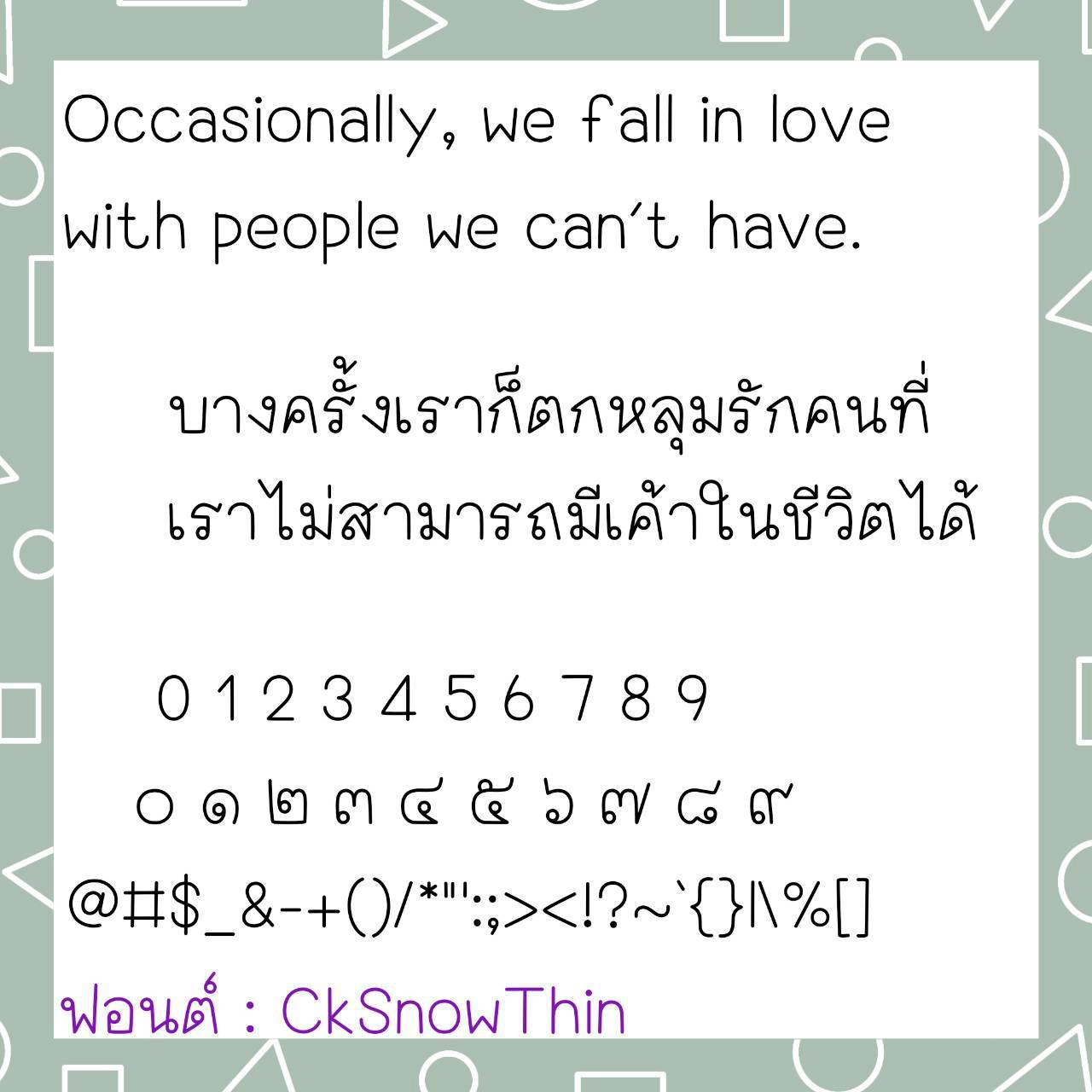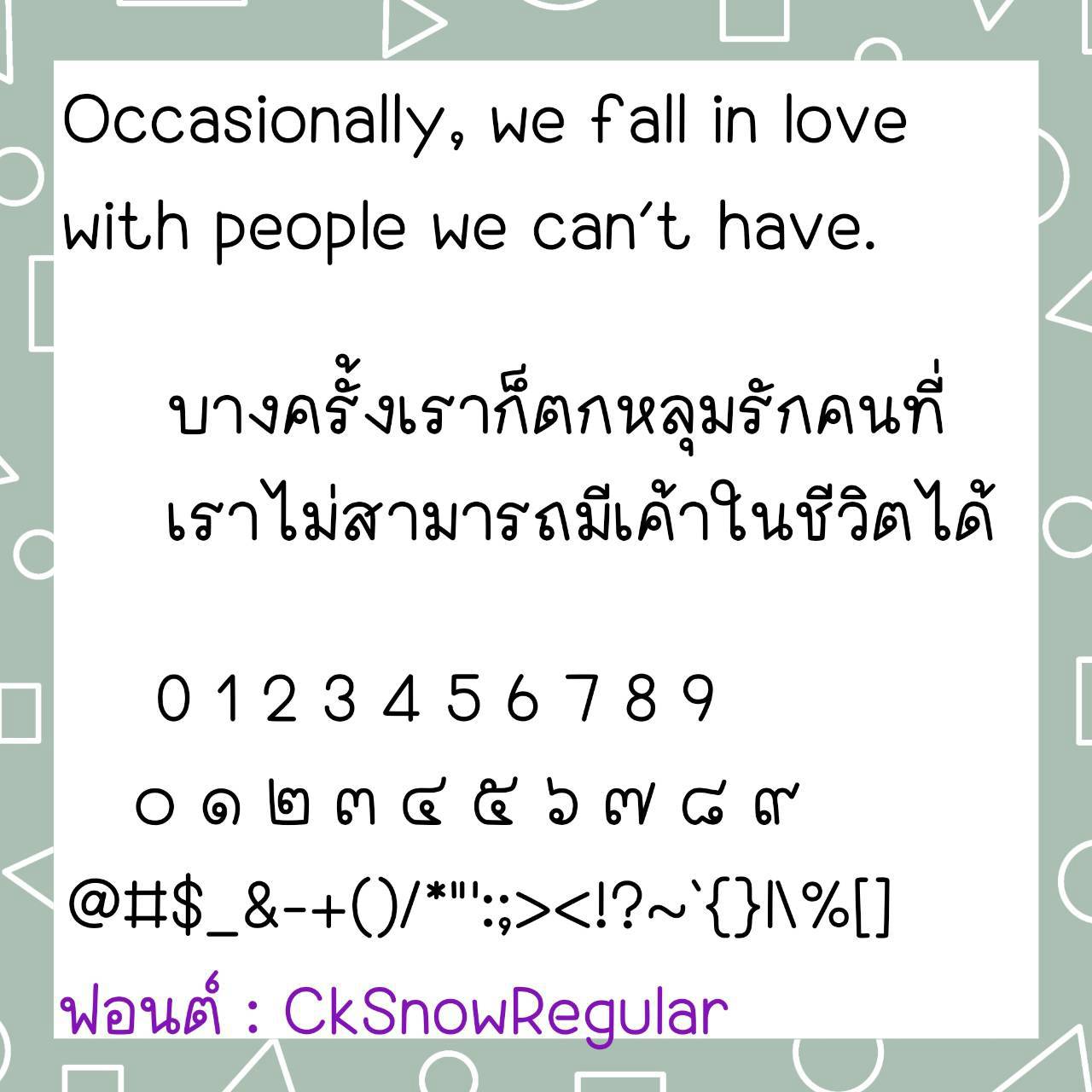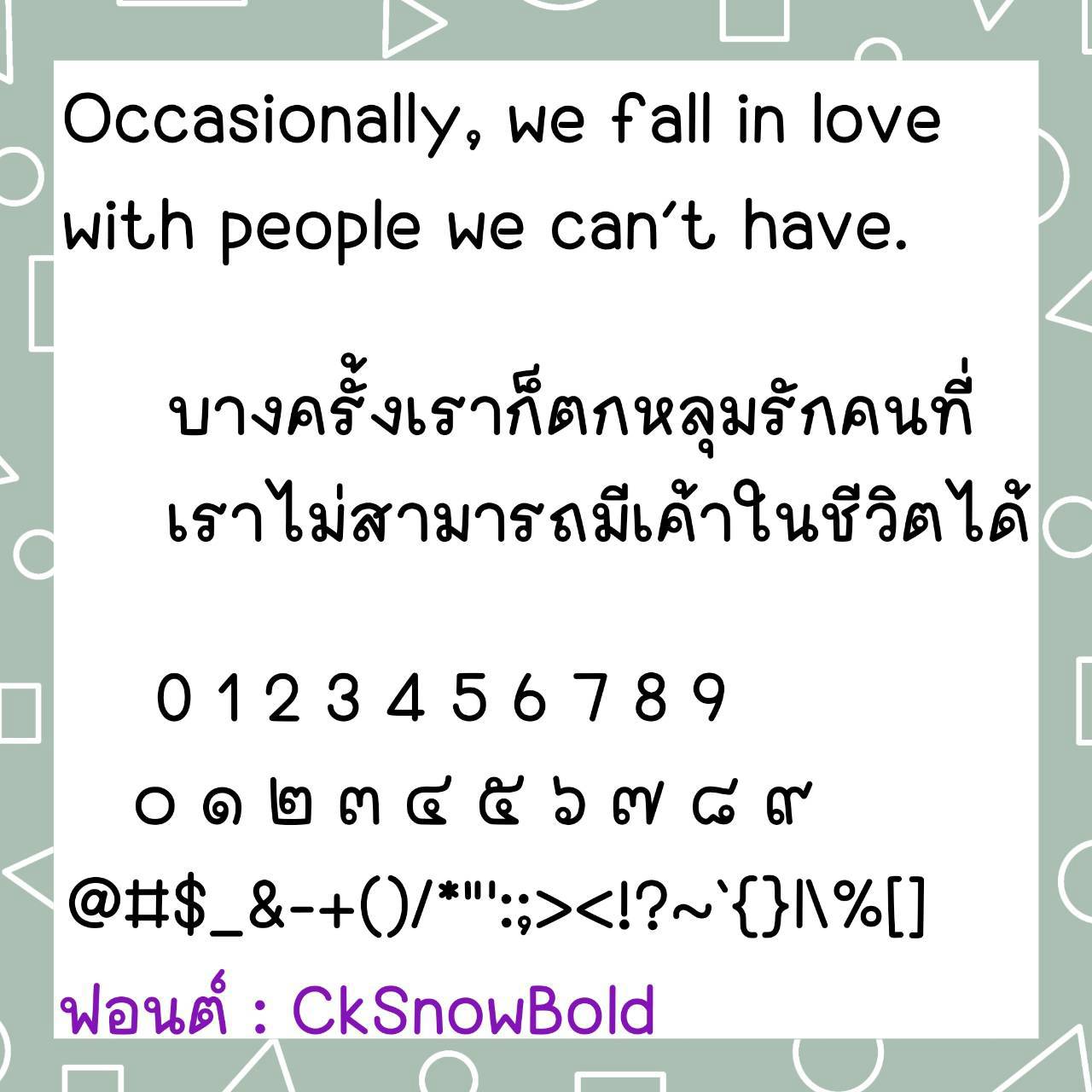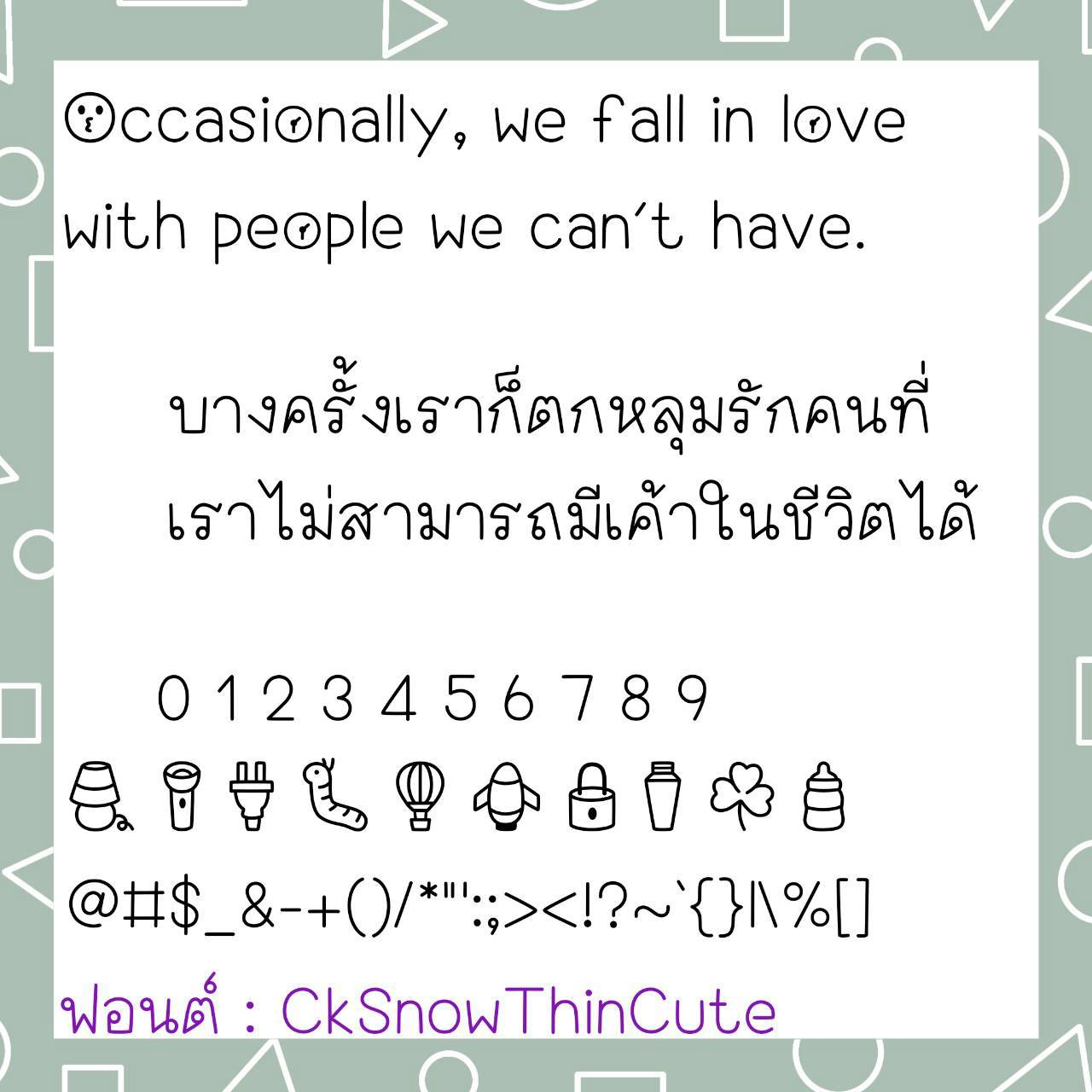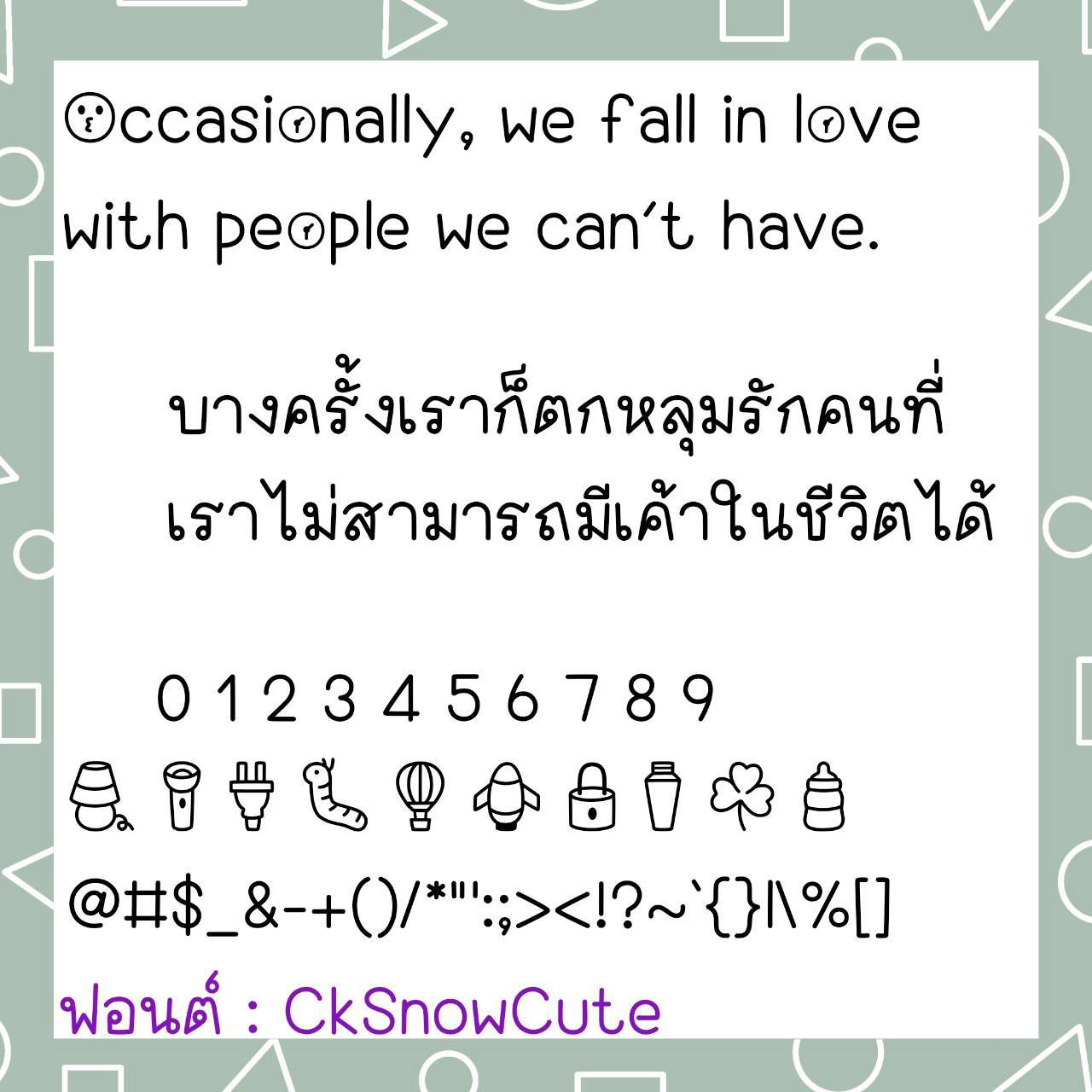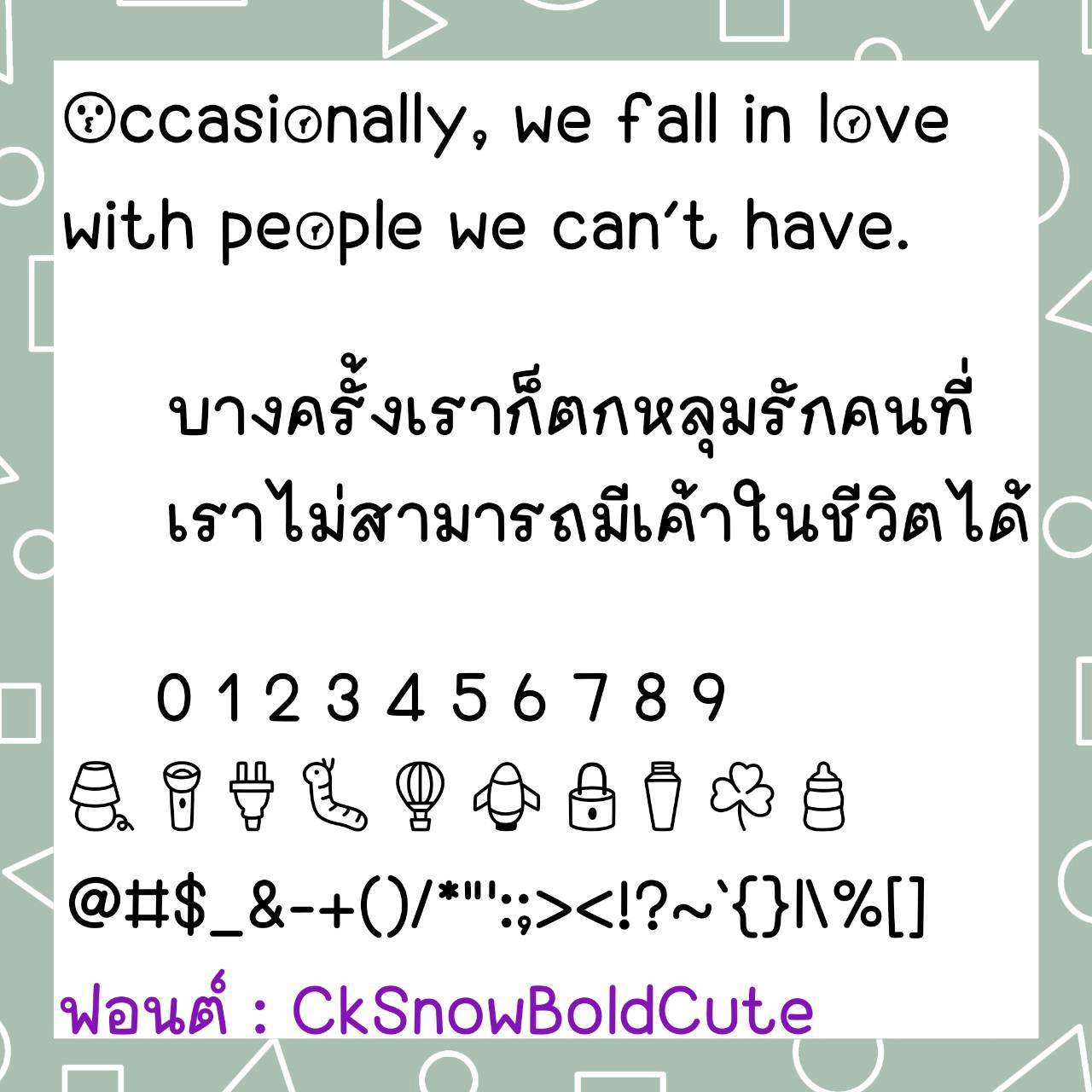
Font CkSnow
ชื่อสินค้า : Font CkSnow 💙
🔸 ฟอนต์ลายมือแนววัยรุ่น มีความยุกยิกดูซนๆแบบมีลูกเล่น ดูไม่น่าเบื่อ แต่ยังอ่านง่าย และยังมีไฟล์อิโมจิน่ารักๆที่ใช้แทนเลขไทยให้ด้วยค่ะ 🥰💙
🔹 This handwritten font has a youthful, playful, and whimsical style that’s anything but boring, yet still easy to read. It also includes cute emoji files that can be used to replace Thai numerals. 🥰💙